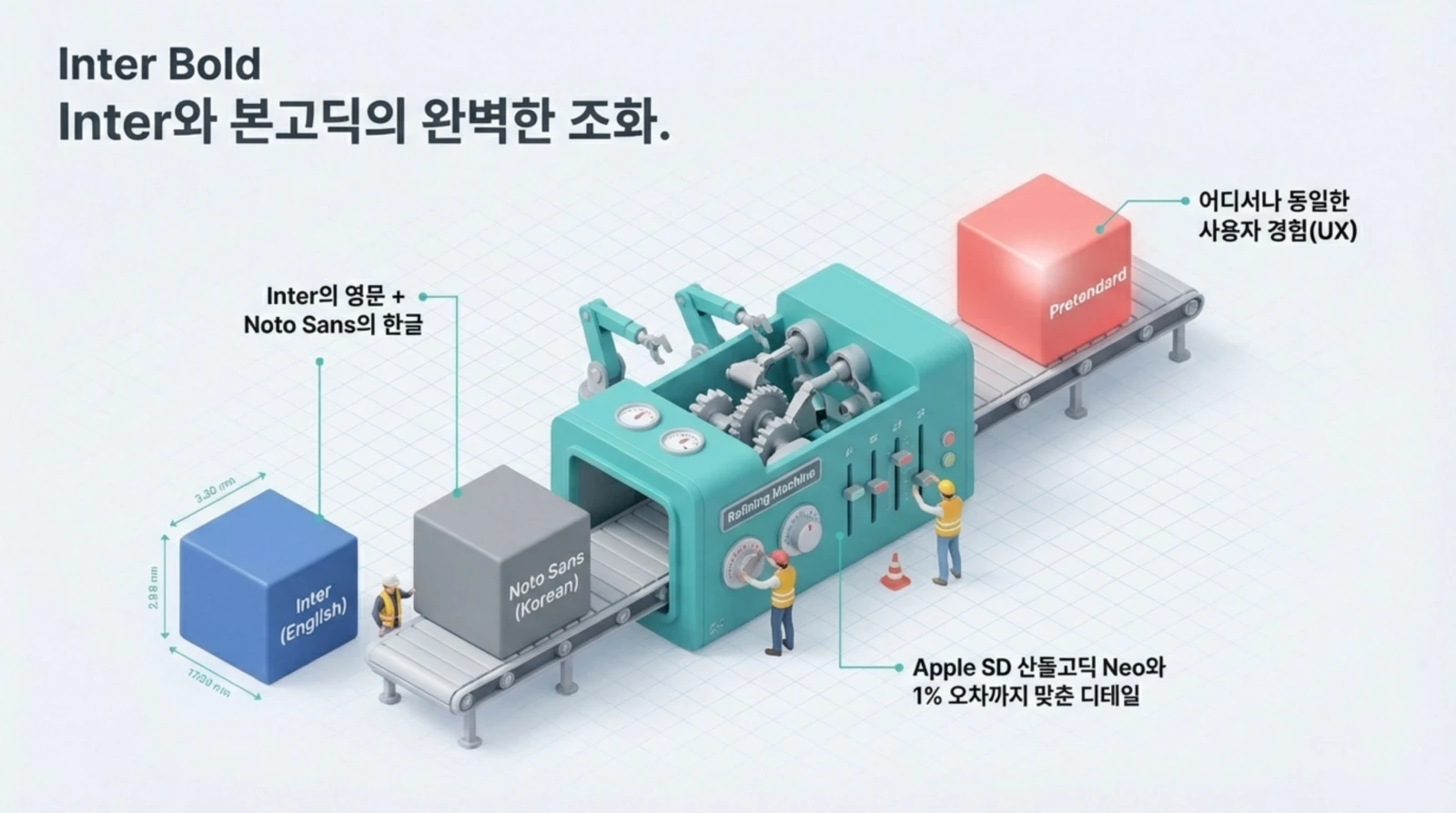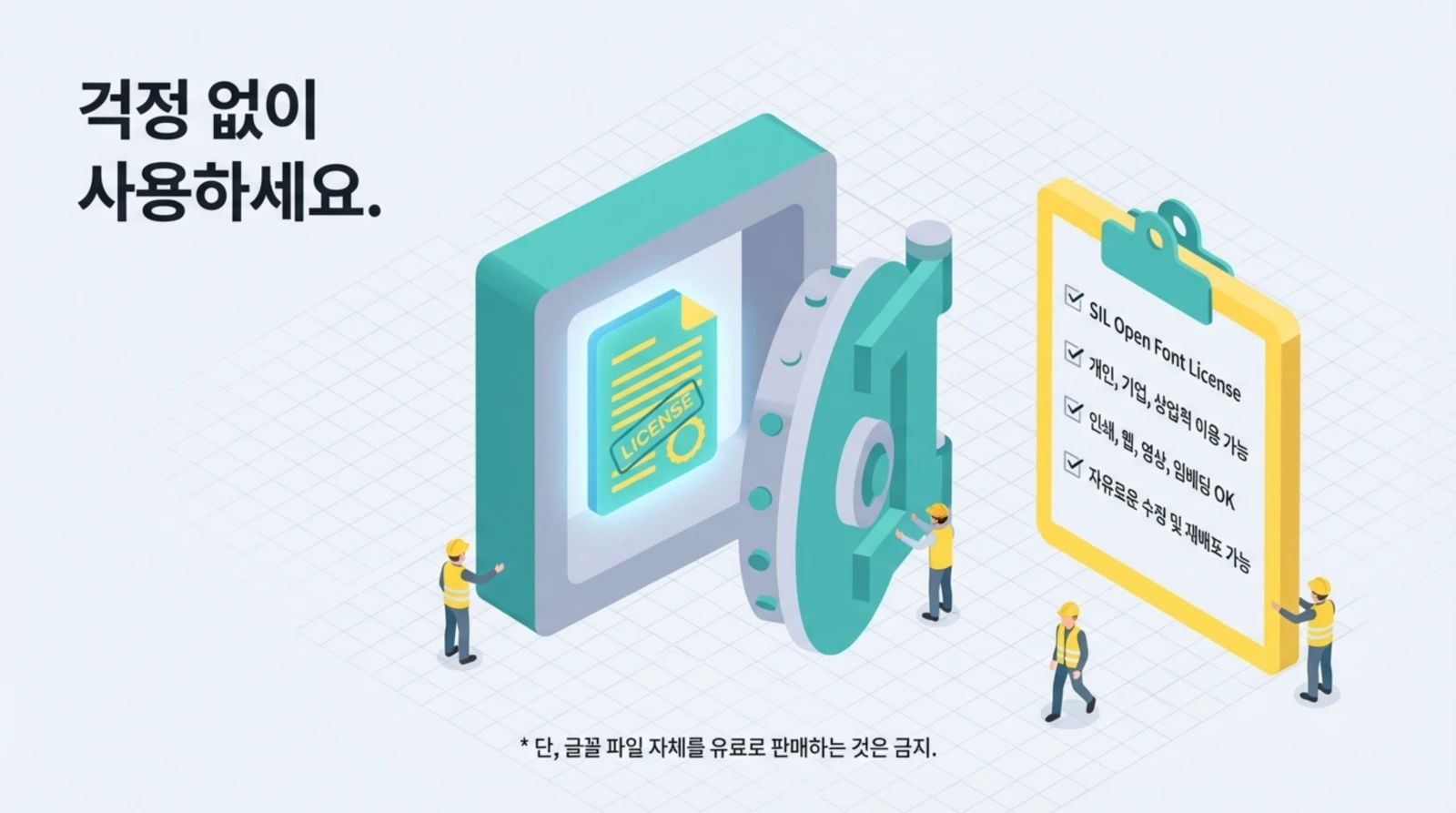
안녕하세요! 여러분, 혹시 웹디자인이나 문서 작업을 하다가 “왜 내 글꼴은 애플 기기에서 보는 것처럼 예쁘지 않지?”라고 생각해보신 적 없으신가요? 저도 예전에 윈도우 환경에서 PPT를 만들 때마다 맑은 고딕의 그 미묘한 답답함 때문에 밤잠을 설쳤던 기억이 납니다. 맥에서 보던 그 정갈한 느낌을 윈도우에서도 구현하고 싶어서 온갖 유료 폰트를 뒤져보기도 했죠.
그러다 만난 것이 바로 이 ‘프리텐다드(Pretendard)’였습니다. 길형진 디자이너가 제작한 이 폰트는 출시 직후부터 디자인 커뮤니티를 뒤흔들었고, 이제는 관공서와 대기업 서비스의 표준 폰트로 자리 잡았습니다. 오늘은 제가 수년간 이 폰트를 실무에 적용하며 느낀 장단점과 함께, 여러분의 작업 퀄리티를 수직 상승시켜 줄 다운로드 가이드를 공유해 드릴게요. 자, 시작해 볼까요? 😊
왜 프리텐다드인가? : 대체 불가능한 3가지 이유 🤔
사실 시중에는 예쁜 무료 폰트가 정말 많습니다. 하지만 프리텐다드가 독보적인 위치를 차지하는 데에는 확실한 이유가 있어요. 제가 생각하는 가장 큰 이유는 바로 ‘시스템 서체와의 완벽한 조화’입니다.
* 애플의 감성을 어디서나: Apple의 San Francisco와 Apple SD 산돌고딕 Neo를 타깃으로 제작되어, 어떤 환경에서도 정갈한 UI를 제공합니다.
* 압도적인 가독성: 본고딕(Noto Sans)을 기반으로 자간과 높이를 미세하게 조정하여 가독성을 극대화했습니다.
* 범용성 끝판왕: 9가지 굵기(Weight)와 180여 개의 언어를 지원하여 전 세계 어디서든 깨지지 않고 출력됩니다.
특히 본고딕(Noto Sans KR)을 써보신 분들은 공감하시겠지만, 영문과 한글을 섞어 쓸 때 글자 크기가 제각각이라 수동으로 자간을 맞추느라 고생한 경험이 있으실 겁니다. 프리텐다드는 이런 ‘기술적 부채’를 해결하기 위해 태어났습니다. 2020년부터 다듬어온 결과물답게, 그냥 타이핑만 해도 전문가가 손을 본 듯한 균형감을 보여주죠.
다운로드에 앞서 내가 필요한 환경에 적합한지 데이터를 통해 확인해 보겠습니다. 프리텐다드는 단순히 글자만 지원하는 것이 아니라, 디자인과 개발 환경 모두를 고려한 고스펙 폰트입니다.
글자가족 및 기술 사양 테이블
| 지원 굵기 | 총 9종 (Thin 100 ~ Black 900) | 본고딕보다 2종 많음 |
| 지원 언어 | 한국어, 영어, 일본어 등 180여 개 언어 | 다국어 환경 최강자 |
정부 공식 서체? Pretendard GOV와 JP 버전 👩💼👨💻
프리텐다드의 진화는 멈추지 않습니다. 최근에는 대한민국 정부의 범정부 UI/UX 디자인 시스템의 기본 서체로 선정되기도 했는데요. 바로 Pretendard GOV 버전입니다.
* GOV 버전: 숫자 고정폭 적용, ‘I’와 ‘l’의 구분 강화 등 가독성이 대폭 개선되었습니다.
* JP 버전: 일본어 환경에서도 어색하지 않도록 가나와 한자 크기를 미세 조정했습니다.
* 가변 폰트(Variable): 하나의 파일로 미세한 굵기 조절이 가능해 트렌디한 디자인에 적합합니다.
공공기관 프로젝트를 하시거나, 다국어 웹사이트를 구축 중이라면 일반 버전보다는 GOV나 JP 버전을 사용하시는 것이 나중을 위해 훨씬 유리합니다. 저도 최근 관공서 협업 프로젝트를 진행하면서 GOV 버전을 썼는데, 확실히 숫자 가독성 면에서 클라이언트의 만족도가 높더라고요.
마무리: 프리텐다드로 디자인에 생명을 불어넣으세요 📝
지금까지 프리텐다드의 매력부터 설치, 활용 팁까지 모두 살펴보았습니다. 폰트는 단순히 글자를 전달하는 도구가 아니라, 브랜드의 신뢰도와 사용자 경험(UX)을 결정짓는 핵심 요소입니다. 무료이면서 이토록 정교한 폰트를 사용할 수 있다는 것은 우리 같은 디자이너와 제작자들에게 정말 큰 축복이죠.